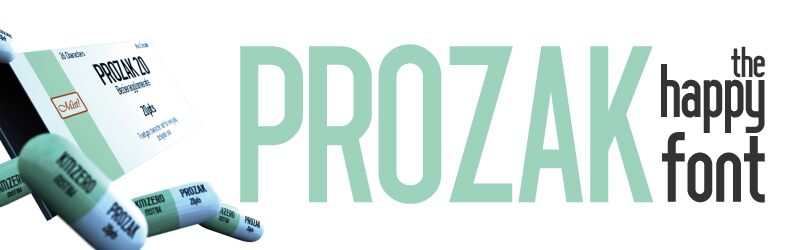
Prozak Light, entworfen von Studio KMzero, ist eine kostenlose schmale Sans-Serif-Schrift mit hohen, eng gezeichneten Buchstaben und einer klaren vertikalen Haltung. Ihre Formen sind sparsam und aufrecht. Abgerundete Kleinbuchstaben mildern die schmalen Proportionen, und die variierenden Strichstärken verleihen der Schrift eine leicht editorielle Note.
Zeitgenössische Kultur und urbane Themen harmonieren mit ihrer schlanken Silhouette, wodurch sie sich für Magazincover, Modemarken, Eventplakate und Albumcover eignet. Unabhängige Verlage, Modelabels und Musikveranstalter werden ihren kompakten, geschliffenen Look besonders gut für bildlastige Arbeiten geeignet finden.